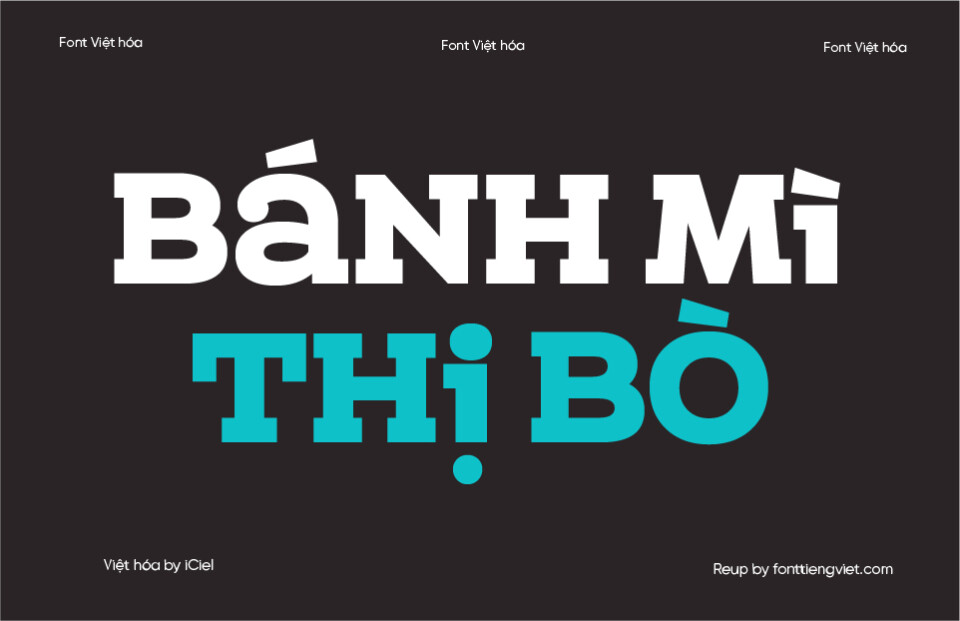
Giới thiệu về Font Việt hóa iCiel Queulat Uni
Trong lĩnh vực thiết kế đồ họa học đường, việc lựa chọn một bộ Font Chữ phù hợp đóng vai trò cực kỳ quan trọng. Font Việt hóa iCiel Queulat Uni là một trong những bộ font slab serif độc đáo, kết hợp hài hòa giữa nét cổ điển và hơi thở hiện đại. Được tối ưu hóa hoàn toàn cho tiếng Việt, bộ font này giúp các bạn học sinh và thầy cô dễ dàng tạo ra những ấn phẩm truyền thông chuyên nghiệp mà không lo lỗi hiển thị dấu câu. Với cấu trúc chữ mạnh mẽ nhưng vẫn giữ được sự mềm mại ở các góc bo tròn, Queulat Uni mang lại cảm giác thân thiện, dễ gần cho người xem.
Ưu điểm nổi bật của Font Việt hóa iCiel Queulat Uni trong học tập
Thiết kế đa năng và linh hoạt
Font Việt hóa iCiel Queulat Uni sở hữu độ dày đa dạng, từ các nét mảnh tinh tế đến các nét đậm chắc chắn. Điều này cho phép người dùng ứng dụng linh hoạt trong nhiều mục đích khác nhau như làm tiêu đề bài thuyết trình PowerPoint, thiết kế bìa báo tường hay trình bày tiểu luận. Đặc biệt, font chữ này có khả năng đọc tốt trên cả màn hình kỹ thuật số và giấy in, giúp nội dung bài học trở nên rõ ràng và lôi cuốn hơn đối với học sinh.
Sự kết hợp hoàn mỹ giữa truyền thống và hiện đại
Lấy cảm hứng từ những kiểu chữ chân phương truyền thống, Queulat Uni đã được cải tiến để trông thanh thoát hơn. Sự sáng tạo này giúp các sản phẩm thiết kế của nhà trường luôn giữ được sự nghiêm túc cần thiết nhưng vẫn mang nét trẻ trung, bắt kịp xu hướng thẩm mỹ hiện nay.
Kết luận và hướng dẫn sử dụng